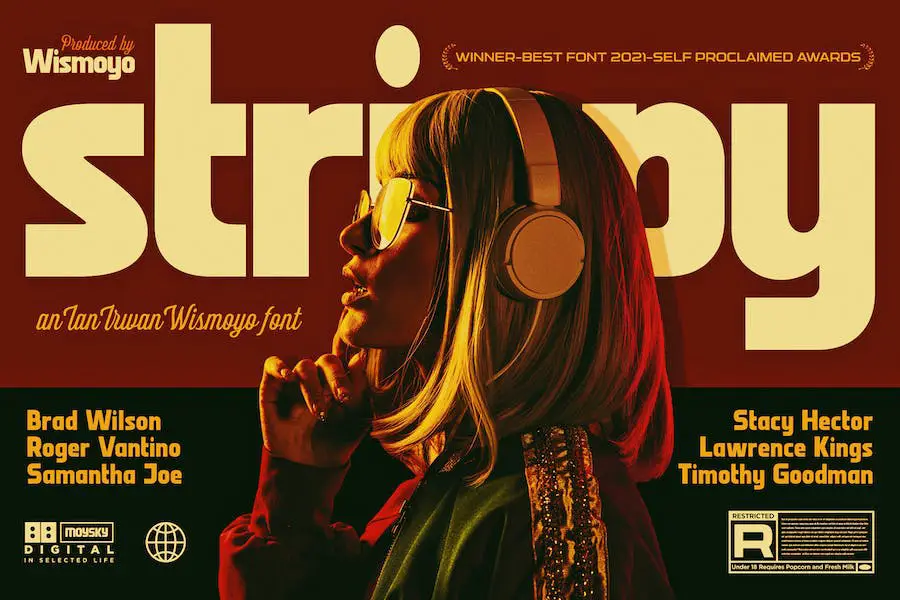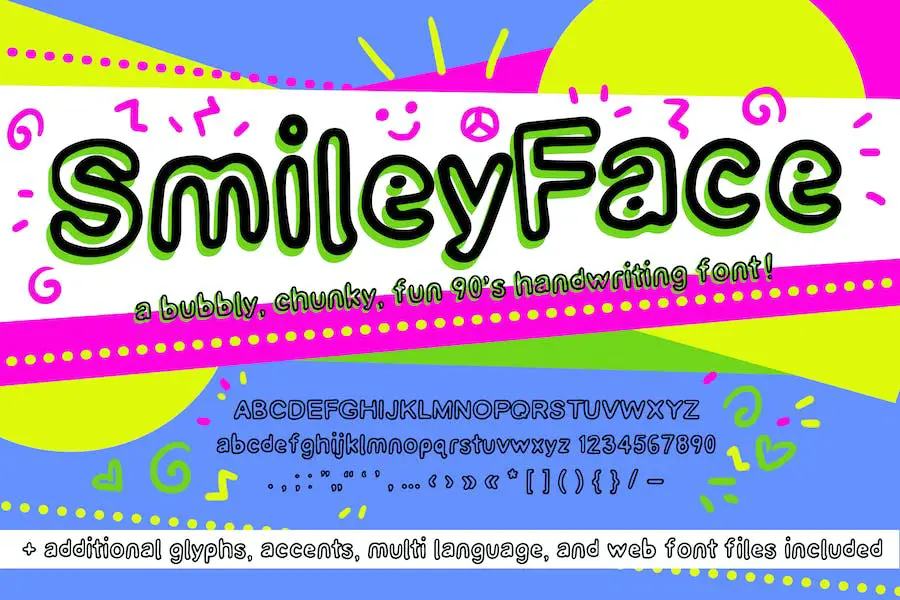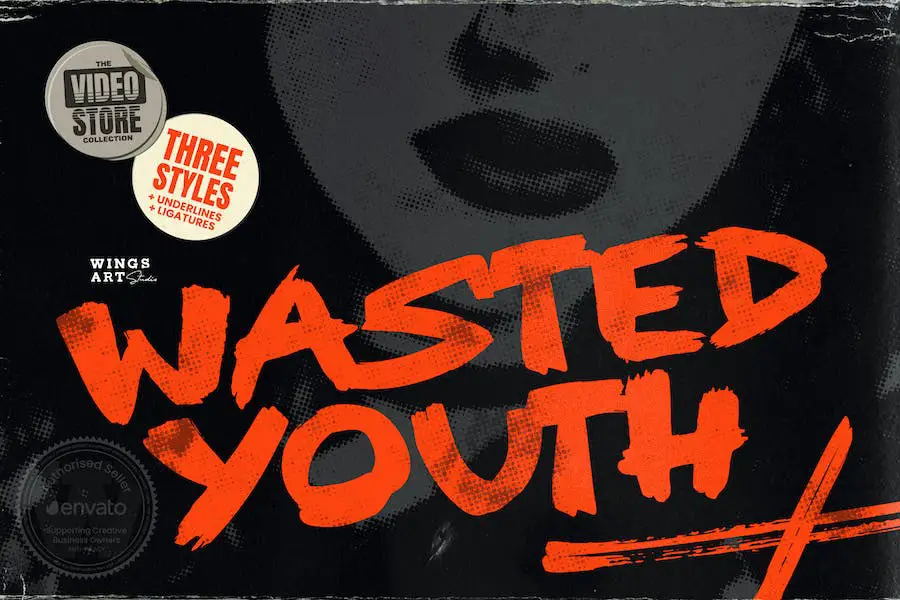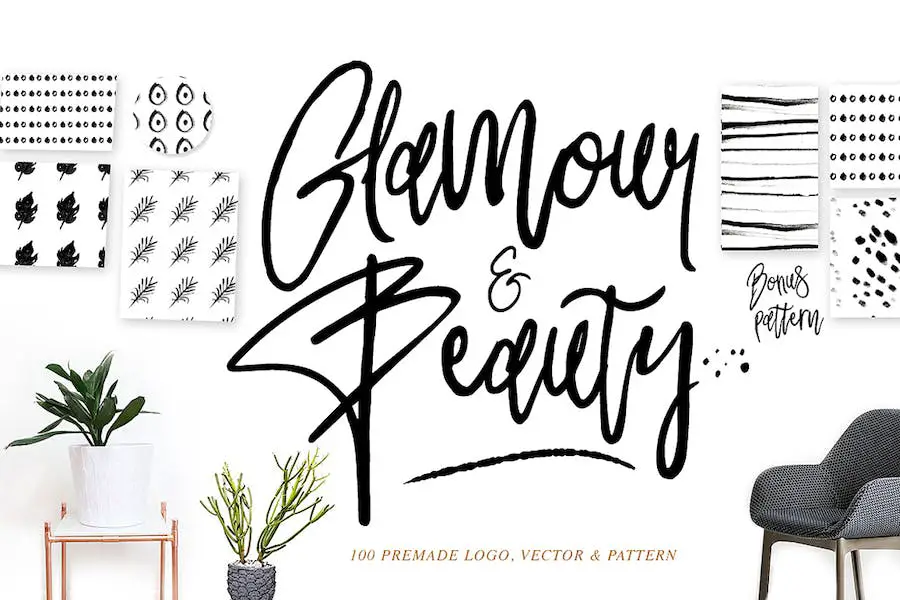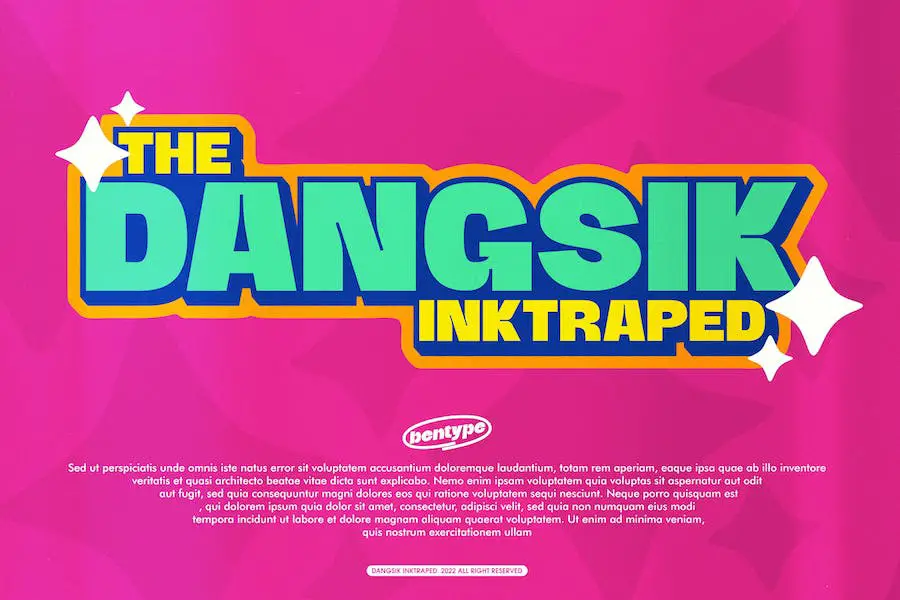
36 meilleures polices des années 90 2023 (gratuites et premium)
Publié: 2023-08-23Êtes-vous un graphiste à la recherche de la police parfaite pour ajouter une touche de nostalgie à vos projets ? Cherchez pas plus loin!
Dans cet article de blog, nous explorerons les 36 meilleures polices des années 90 de 2023, garanties pour rehausser vos créations et transporter votre public dans l’ère emblématique des années 90.
Maintenant, vous vous demandez peut-être pourquoi les polices des années 90 ? Eh bien, les années 90 étaient une époque de design audacieux, dynamique et expressif. De la typographie grunge aux lettres néon funky, les polices des années 90 ont capturé l'esprit de la décennie comme aucune autre.
L'intégration de ces polices dans vos projets ajoute non seulement une touche tendance et rétro, mais exploite également le facteur nostalgie si populaire aujourd'hui.
Dans cet article, nous plongerons dans le monde des polices des années 90 et présenterons les 36 meilleures options à considérer. Que vous travailliez sur un projet de branding, une affiche ou un site Web, nous avons ce qu'il vous faut.
Préparez-vous à explorer un large éventail d'options, des polices originales et ludiques aux polices élégantes et minimalistes. Alors plongeons-nous et découvrons les meilleures polices des années 90 pour améliorer vos projets de conception en 2023.
Meilleures polices premium des années 90
Faites un voyage dans le passé et explorez les meilleures polices premium des années 90 disponibles aujourd’hui. Découvrez les produits suivants pour ajouter une touche de nostalgie et sublimer vos projets de conception graphique.
Os de la mère
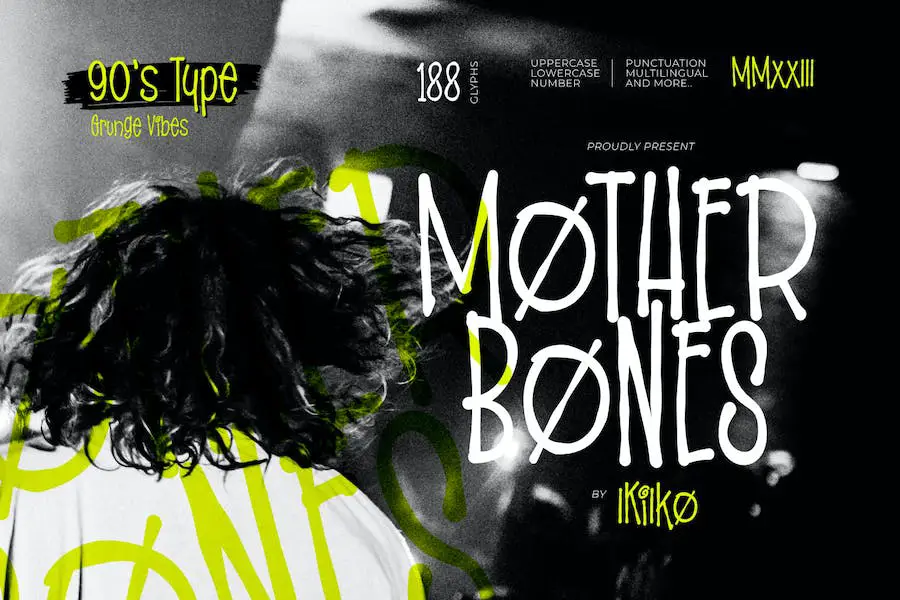
Mother Bones est une police polyvalente qui peut élever vos projets de conception graphique à un tout autre niveau.
Que vous travailliez sur une affiche, une mise en page de magazine, un logo de marque, une couverture de pochette, un dépliant de fête ou que vous ayez simplement besoin d'une superposition de texte élégante pour n'importe quelle image d'arrière-plan, cette police est parfaite pour le travail.
S'inspirant du style d'écriture des années 90, Mother Bones capture l'essence de l'époque où le son de Seattle dominait la scène musicale.
Le puéril
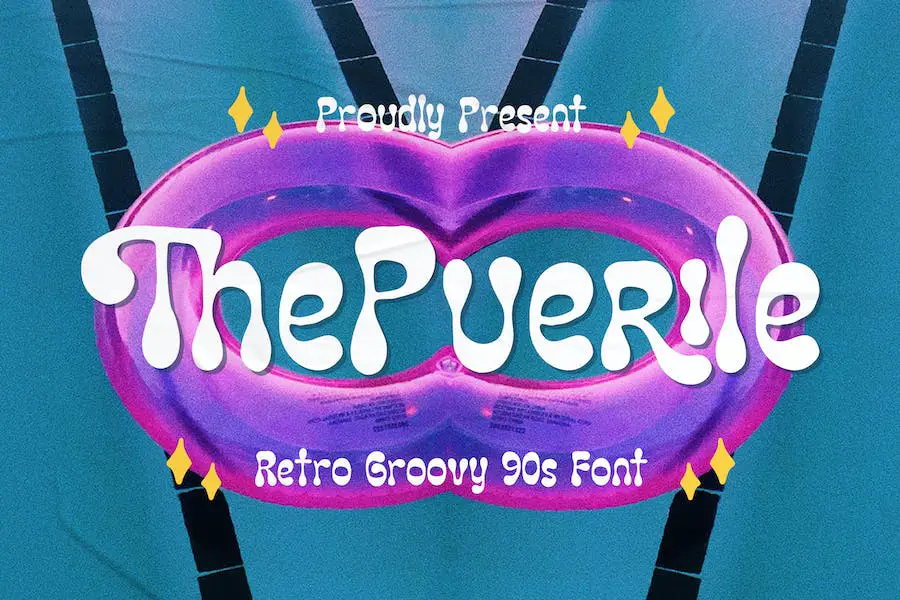
Le Puerile est une police rétro groovy connue pour sa capacité à vous transporter dans l’ère nostalgique des années 90. Avec son esthétique ludique et vintage, cette police d'affichage est parfaite pour ajouter une touche rétro spéciale à tout projet de design que vous avez en tête.
Que vous soyez un graphiste travaillant sur un site Web, un dépliant ou même un dessin de tatouage, The Puerile est là pour élever votre projet au niveau supérieur. Son style unique et son côté nostalgique capteront certainement l'attention de votre public.
Enregistrer Scratch
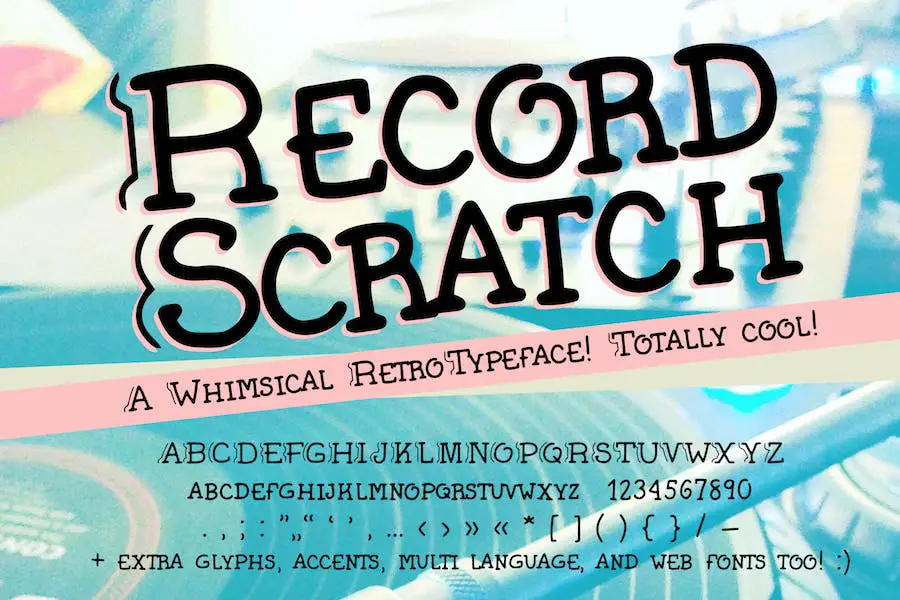
Record Scratch est une police rétro appelée « It » qui s'inspire de la musique indépendante et des vieux disques. Si vous êtes fan des polices des années 80 ou 90, des éléments décoratifs de vos polices et des polices d'écriture manuscrites uniques, alors cette police est parfaite pour vous.
Le créateur de cette police s'est inspiré de son magasin de disques d'occasion préféré de sa jeunesse, lui donnant une touche nostalgique et vintage.
Cela leur rappelle même une vieille sitcom ! Une caractéristique unique de cette police est qu’elle est superbe lorsqu’elle est utilisée avec des couleurs superposées, ce qui en fait une police d’affichage amusante et accrocheuse.
Garage Est
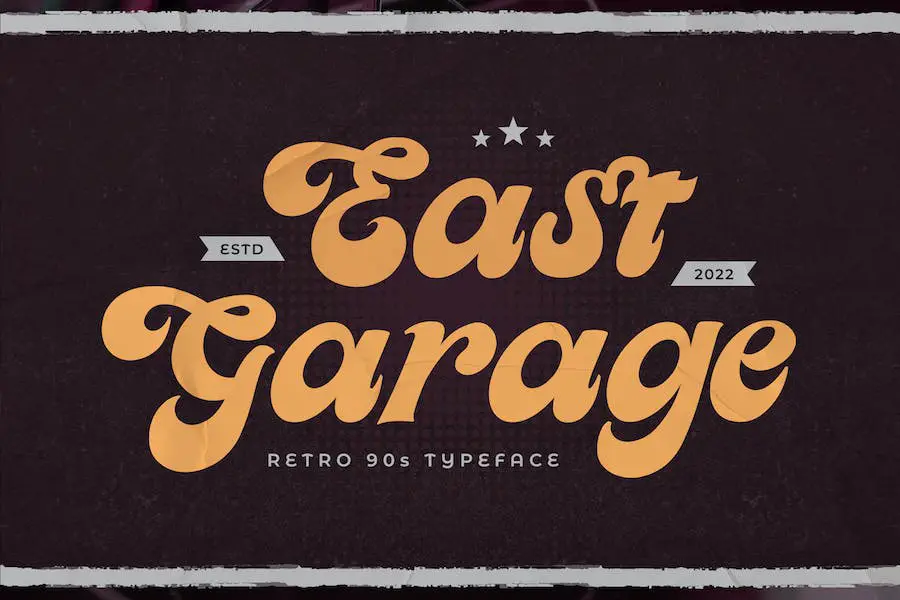
East Garage est une police décorative rétro qui vous ramène instantanément à l'atmosphère vibrante et nostalgique des années 90. Avec son esthétique ludique et vintage, cette police d'affichage est le complément parfait à tout projet de design nécessitant une touche de charme rétro.
Que vous travailliez sur une affiche, un logo ou toute autre idée créative, cette police ajoutera cette touche spéciale des années 90 et élèvera votre design à un autre niveau. Préparez-vous à libérer votre créativité et faites un voyage dans le passé avec East Garage !
Parc permanent
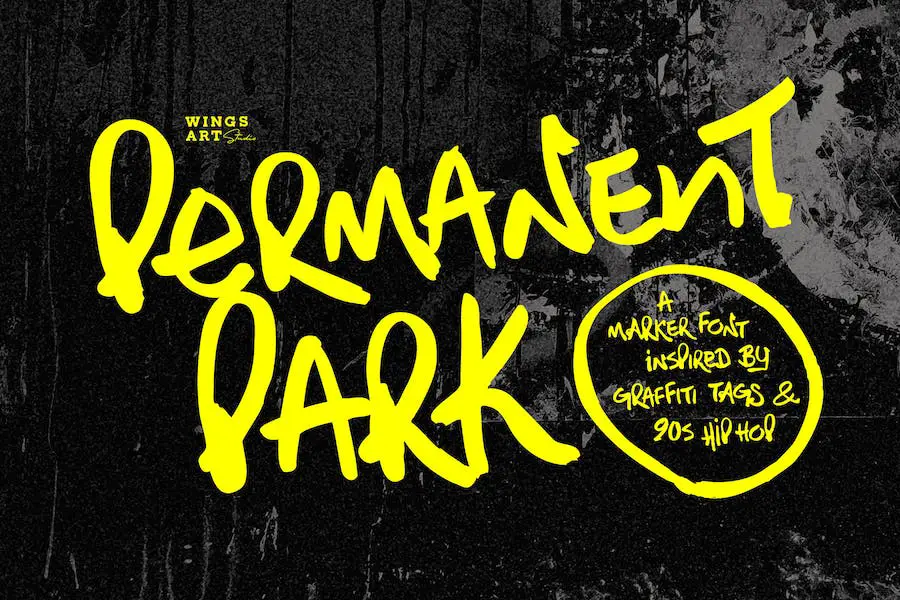
Permanent Park est une police qui apporte une ambiance urbaine unique à vos créations, qui rappelle les vidéoclips et les émissions de télévision des années 90. Que vous travailliez sur des affiches, des titres de films, des emballages de produits ou même des émissions et de la publicité, cette police est parfaite pour ajouter une touche de nostalgie et de style.
Ce qui distingue Permanent Park, c'est sa personnalisation. Il offre un ensemble complet de caractères majuscules et minuscules, ainsi que des chiffres, des signes de ponctuation et une prise en charge linguistique.